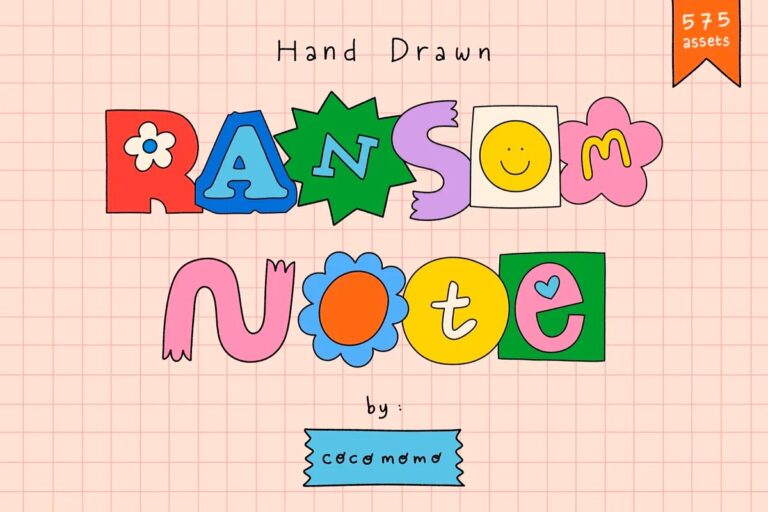
Rất vui mừng được giới thiệu đến các bạn bộ Hand Drawn Ransom Note Letter. Gói nội dung bao gồm 575 thành phần bao gồm các chữ cái, số và dấu câu. Đồ họa đầy màu sắc vui nhộn để trang trí cho các dự án của bạn. Sử dụng đơn giản, dễ dàng chỉ cần kéo và thả! Tất cả các file đều ở định dạng .PNG với độ phân giải chất lượng cao.